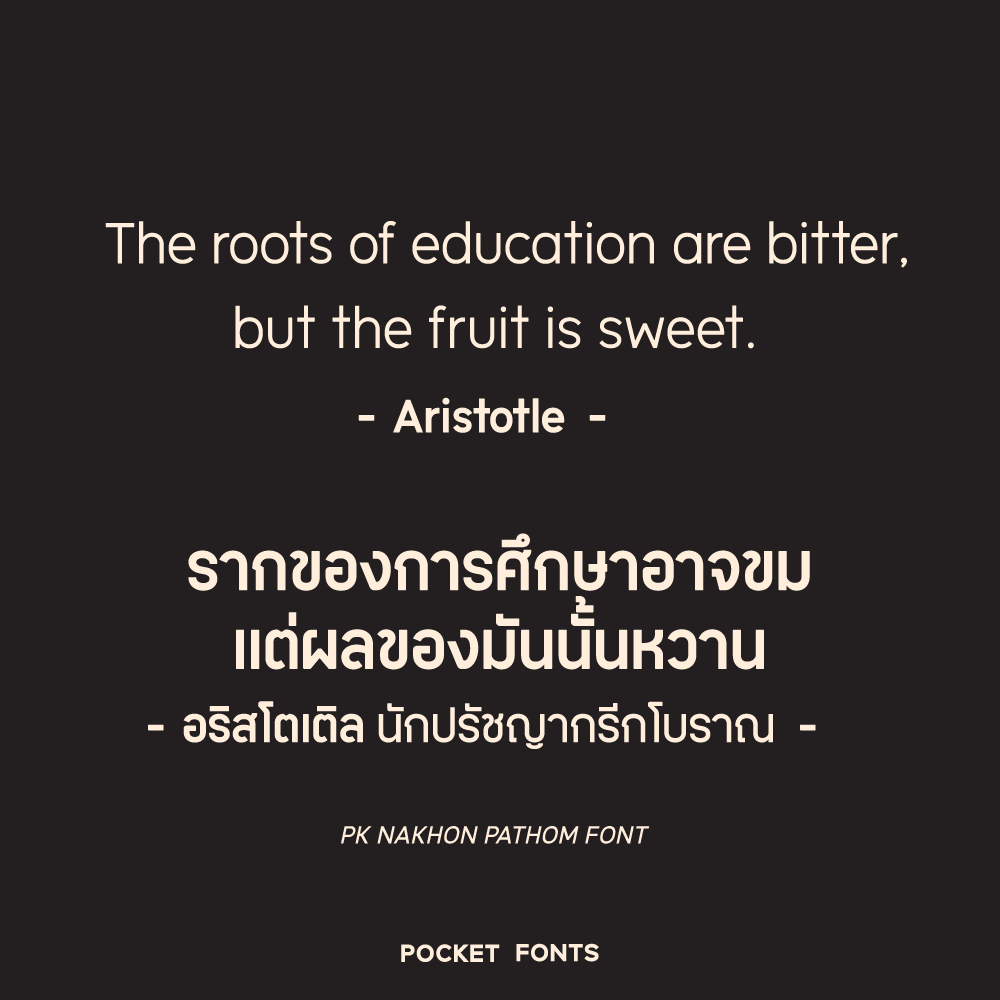
พีเค นครปฐม | PK Nakhon Pathom
ชื่อฟอนต์ พีเค นครปฐม | PK Nakhon Pathom
พีเค นครปฐม ฟอนต์โมเดิร์น มินิมอลที่ดูเรียบง่าย เป็นระเบียบ ทันสมัย โดดเด่นในทุกการใช้งาน เข้ากับคอนเทนต์ยุคใหม่ ไม่ว่าจะเป็นงานออกแบบ สื่อสิ่งพิมพ์ หรือคอนเทนต์ออนไลน์ ให้ทุกตัวอักษรของคุณสื่อสารได้อย่างชัดเจนและทันสมัย เสริมสร้างความน่าประทับใจให้กับทุกโปรเจกต์อย่างไร้ขีดจำกัด มีทั้งหมด 5 น้ำหนัก + Variable